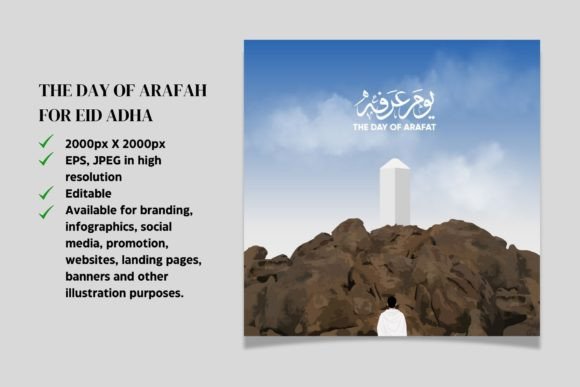
The Day of Arafah for Eid Adha
การค้นหาองค์ประกอบการออกแบบที่เหมาะสมอาจเป็นเรื่องท้าทาย แต่ The Day of Arafah for Eid Adha นำเสนอคอลเลกชันที่โดดเด่นซึ่งช่วยยกระดับงานของคุณได้ทันที
ไม่ว่าคุณจะสร้างผลิตภัณฑ์ POD (Print on Demand) คำเชิญงานแต่งงาน หรือกราฟิกโซเชียลมีเดีย The Day of Arafah for Eid Adha ก็เหมาะสมอย่างยิ่ง